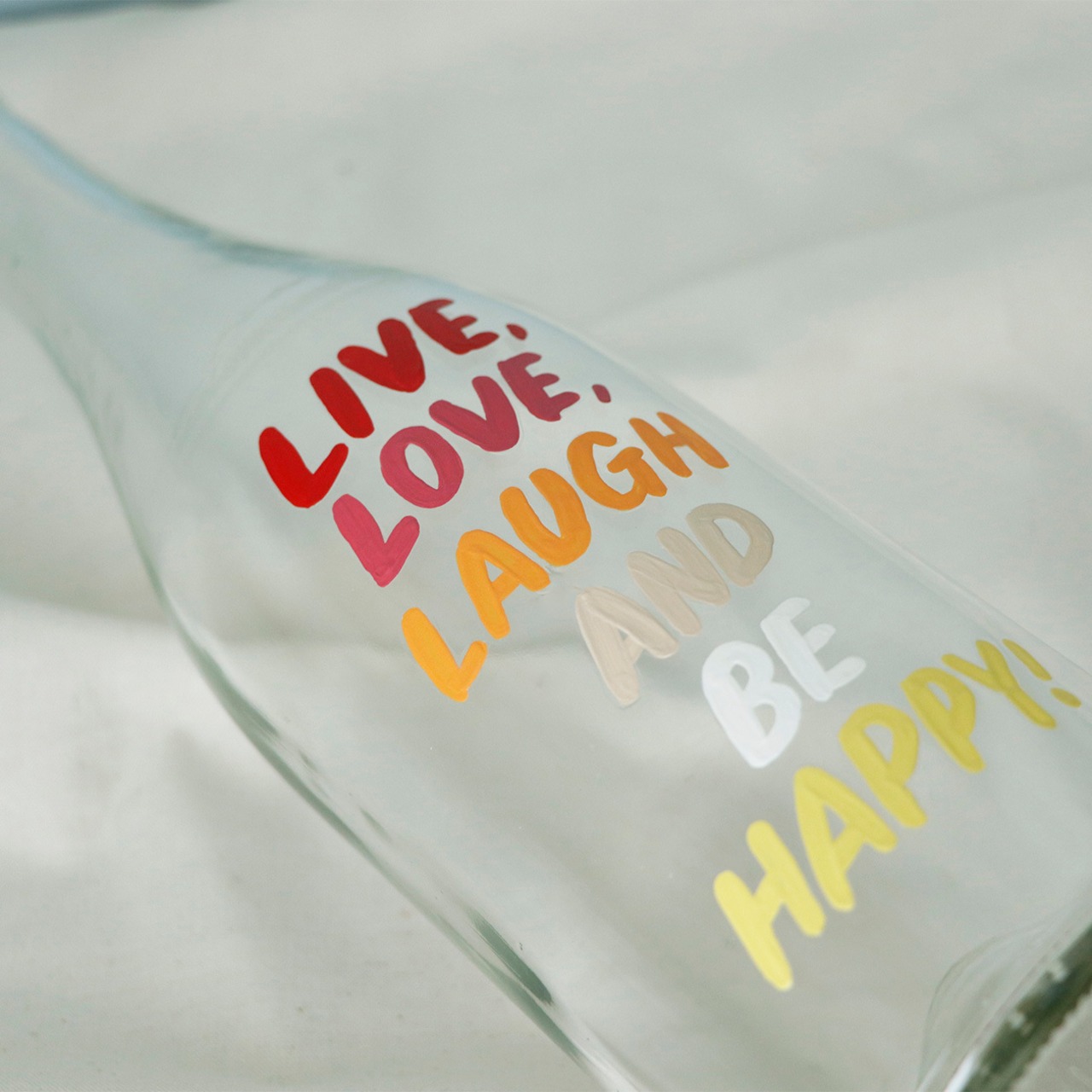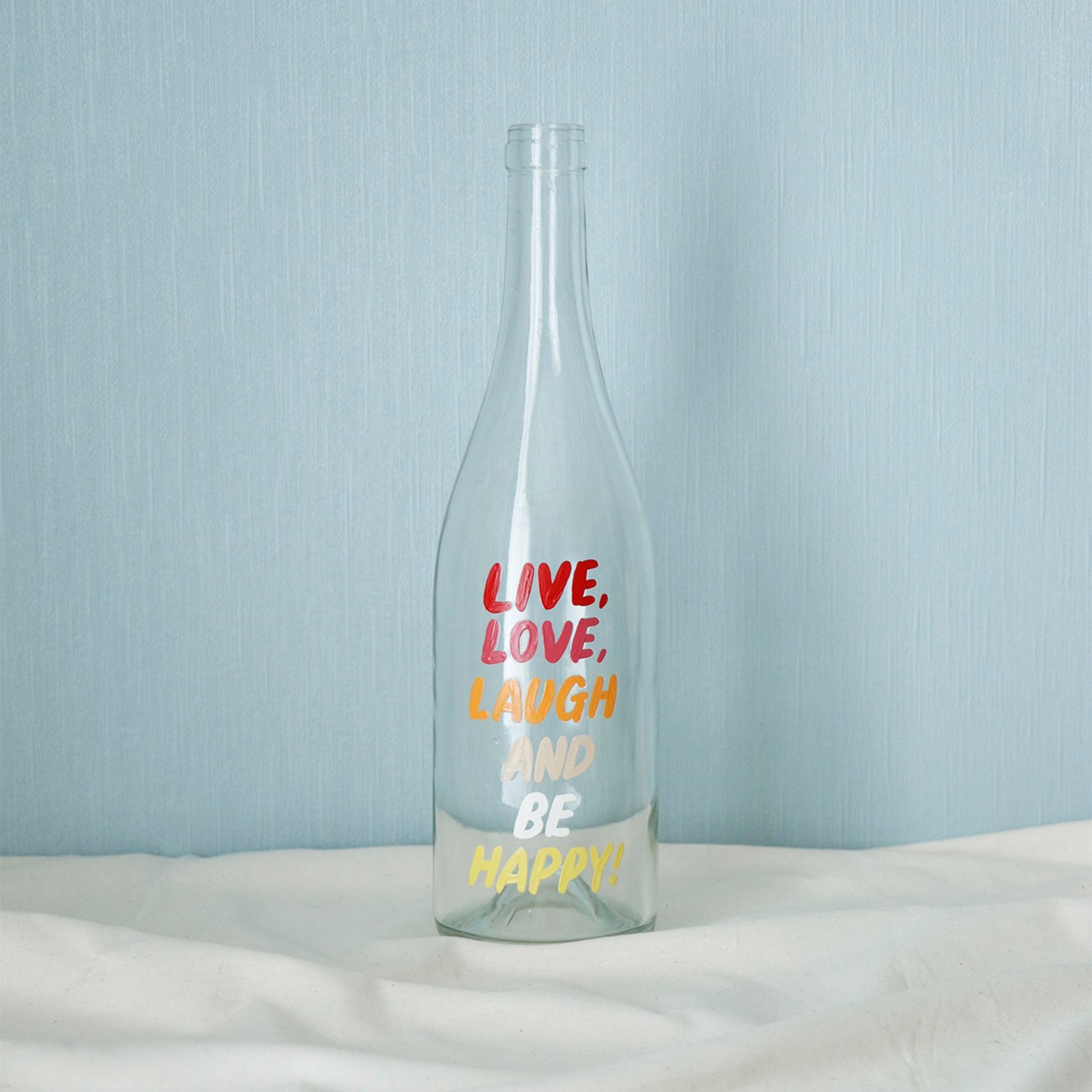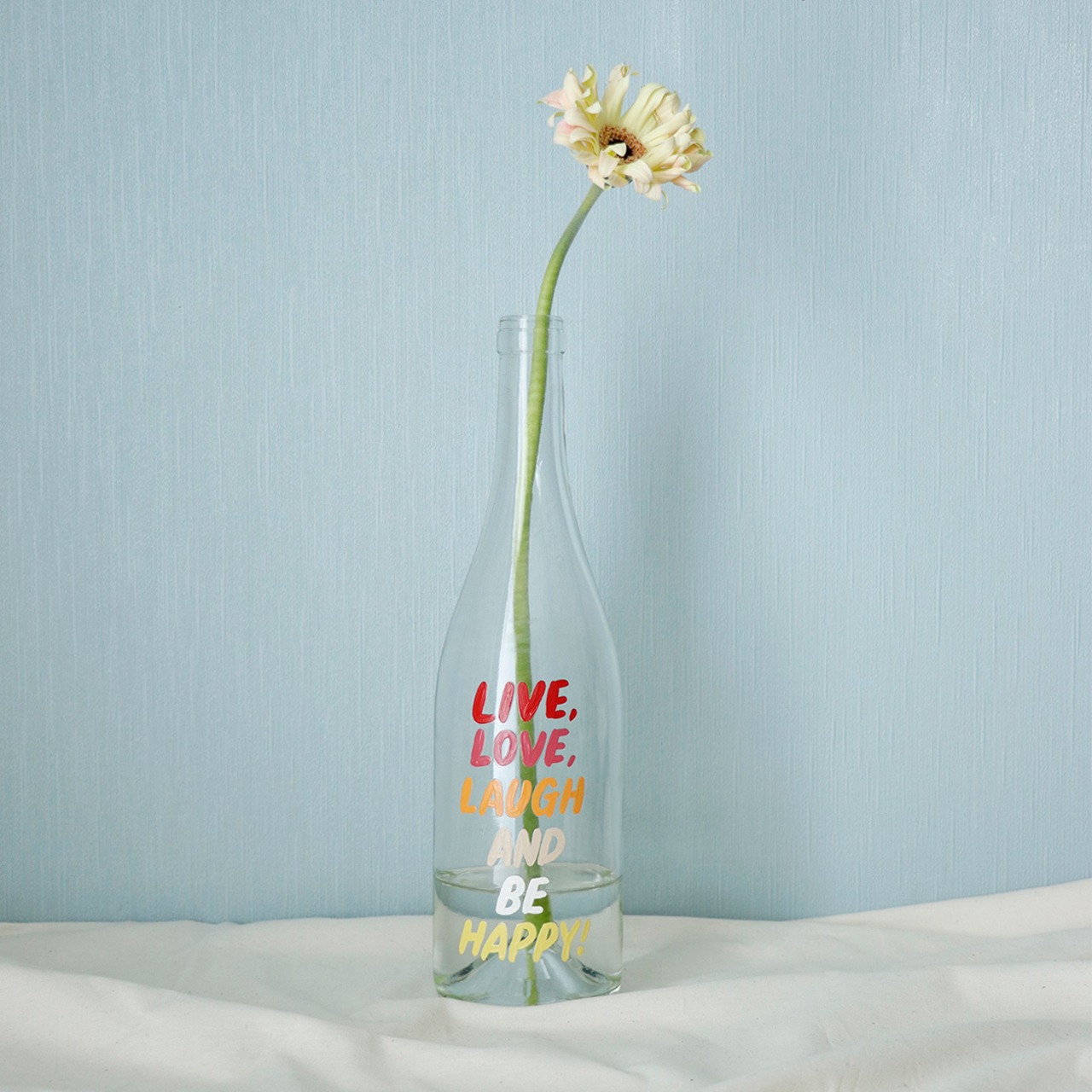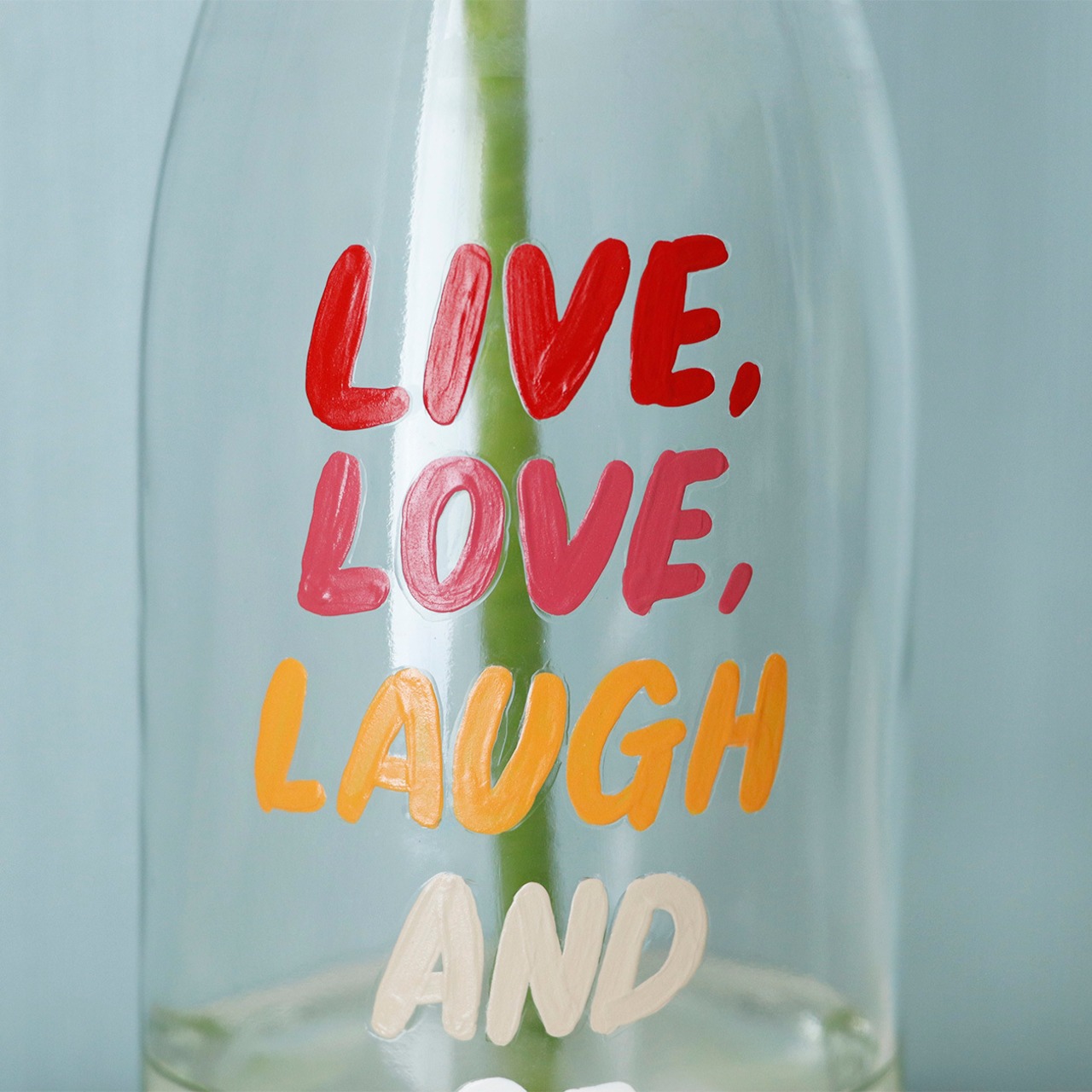
【BOTTLE PAINT ART】LIVE,LOVE,LAUGH,AND BE HAPPY! 07
LIVE,LOVE,LAUGH,AND BE HAPPY!
愛して 笑って ハッピーな人生を!
試作で作った時から人気!なこの言葉。
ボトルを変え、色を変え、人気すぎて気付いたら7本目です。
今回はアクリルキーホルダーと同じ色!!まさにHAPPYになりそうなカラーです。
光が入るとこに置くと、瓶の色とともに文字も影になって素敵ですよ!!
空き瓶に文字を直接ペイントしています。クリアコーティングしていますが、引っ掻きに弱いので取扱いの際はご注意ください。